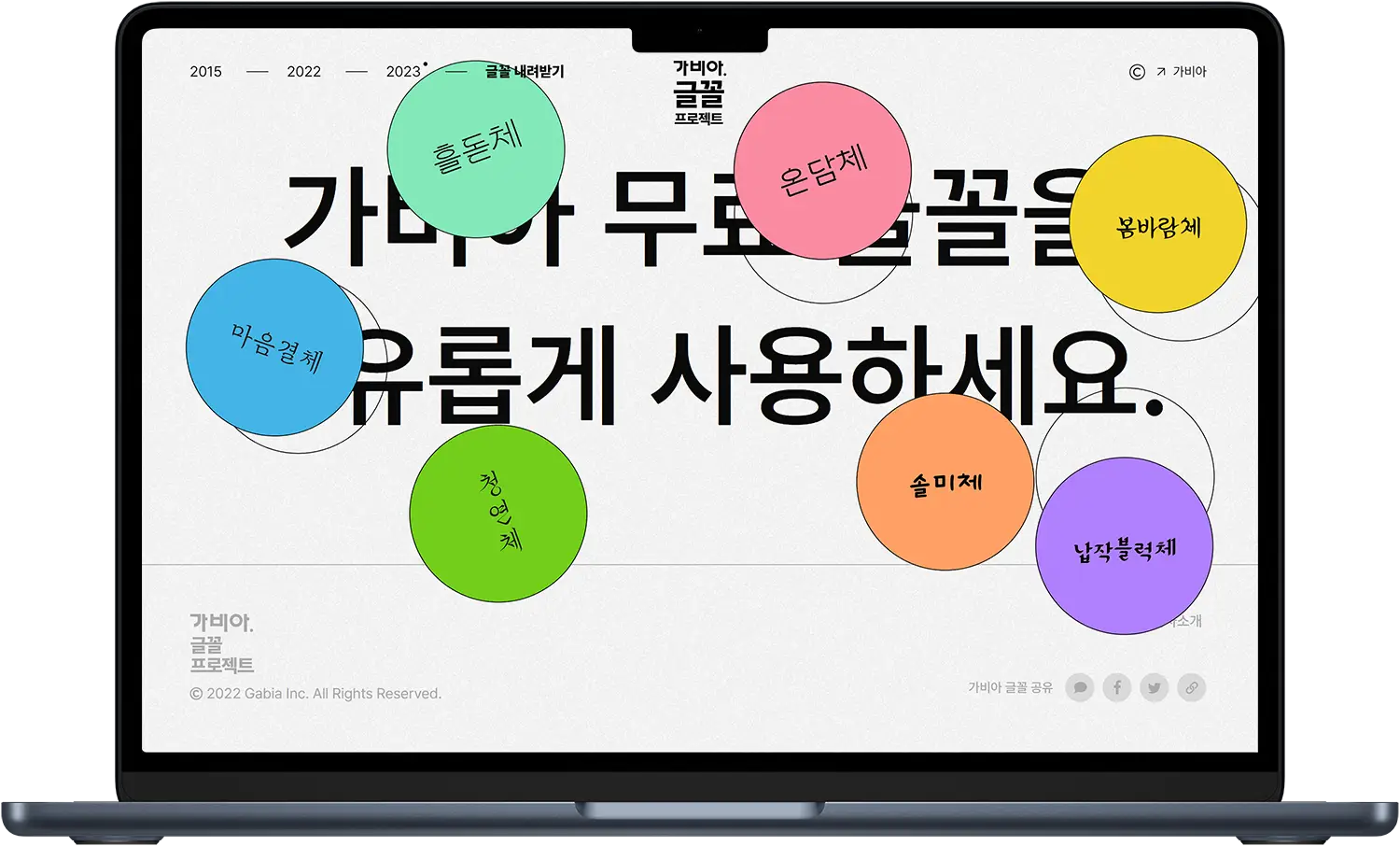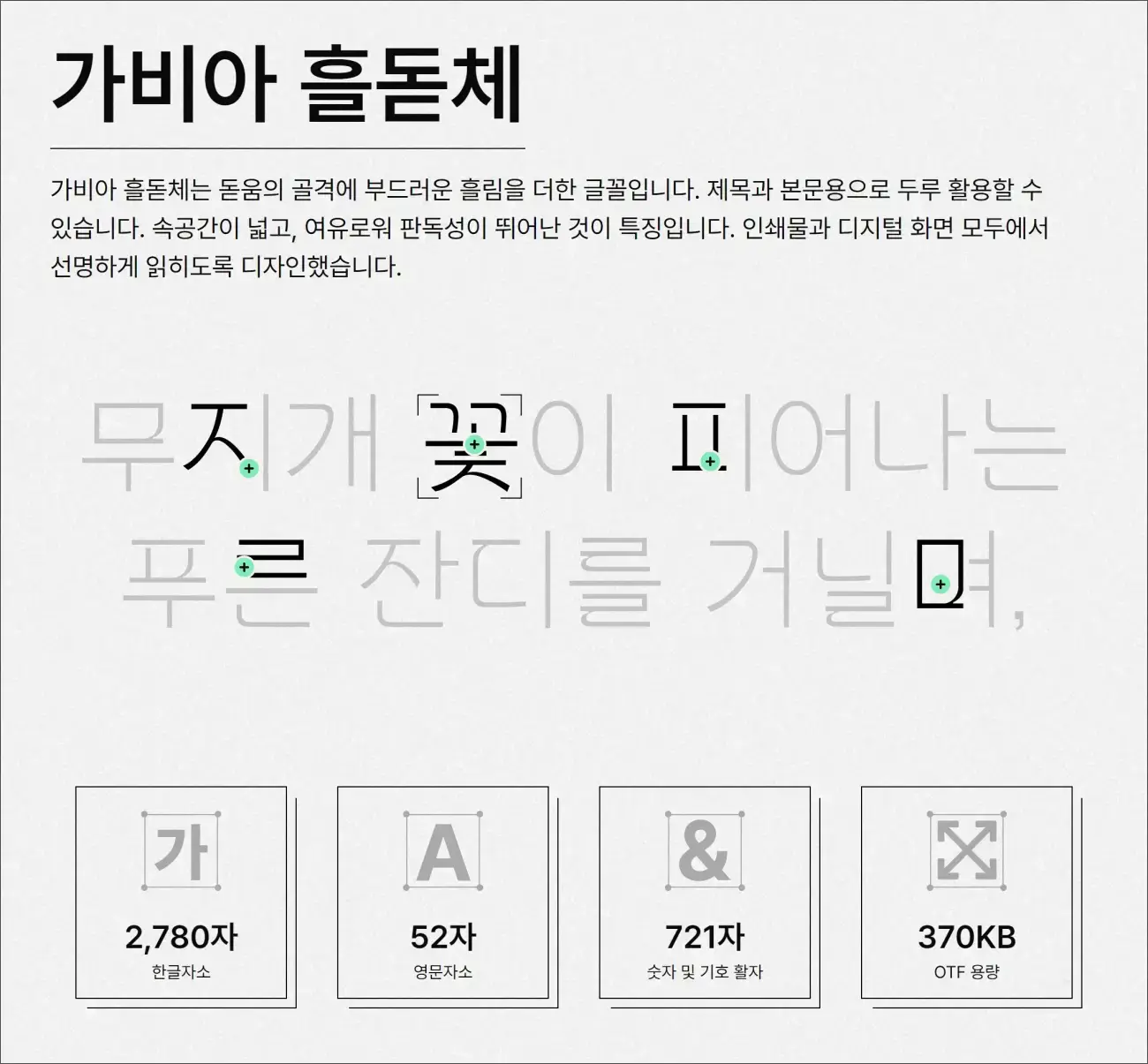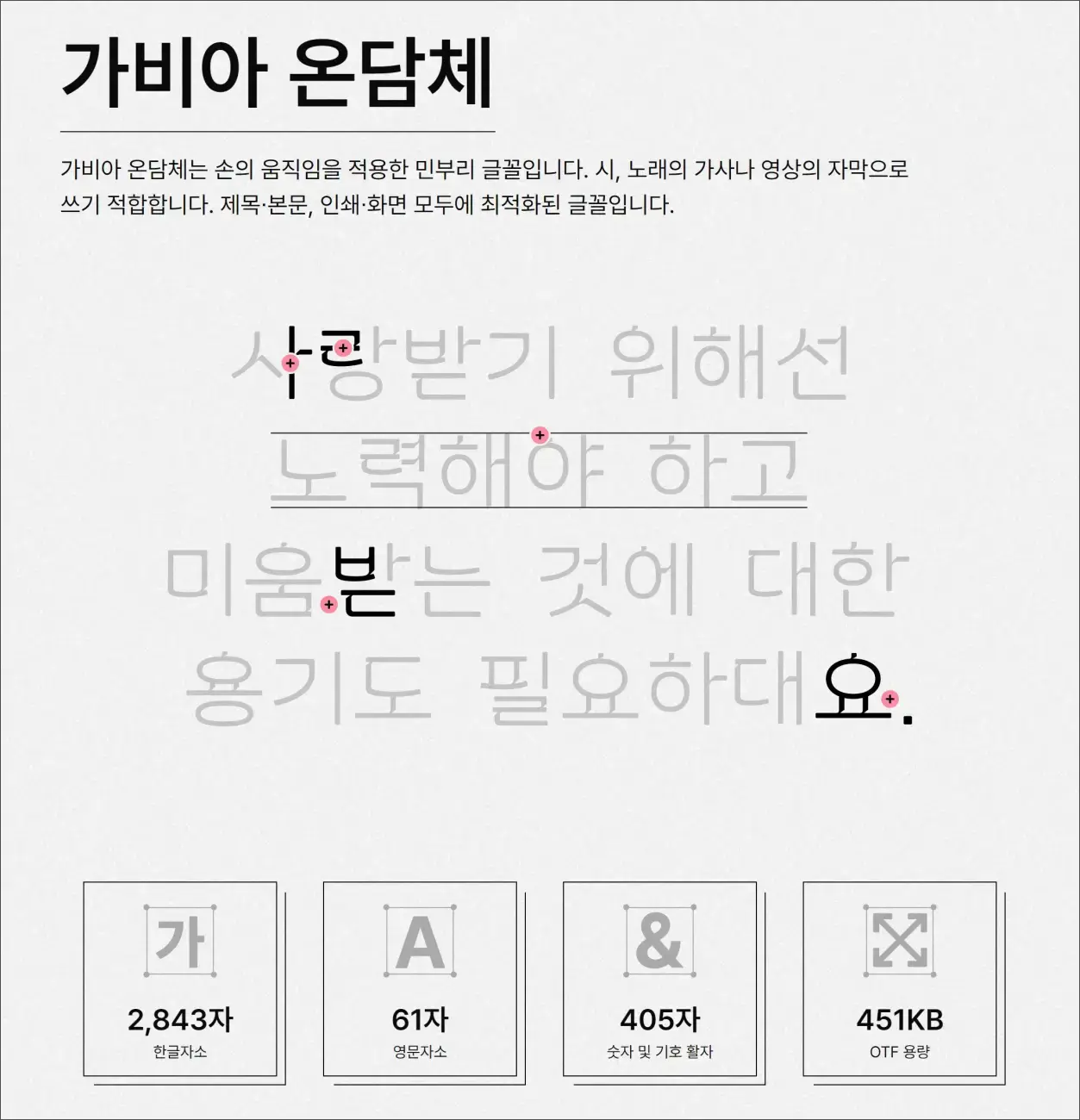
"가비아 흘돋체, 온담체 무료 다운로드 한글폰트 상업적 사용 가능"
클라우드 전문 기업 가비아는 '가비아 글꼴 나눔 프로젝트'로 지난 2015년과 2022년에 이어 2023년에 가비아 흘돋체, 온담체 두 개의 무료 한글 폰트를 공개했습니다. 개인이나 기업 구분 없이 누구나 자유롭게 상업적 목적에도 사용할 수 있지만, 글꼴 자체를 유료로 판매하거나 수정 및 재배포는 할 수 없습니다.
가비아 무료 한글폰트 흘돋체
가비아 흘돋체는 돋움의 골격에 부드러운 흘림을 더한 글꼴입니다. 제목과 본문용으로 두루 활용할 수 있으며 인쇄물과 디지털 화면 모두에서 선명하게 읽히도록 디자인되었습니다.
가비아 흘돋체는 한글자소 2,780자, 영문자소 52자, 숫자 및 기호 721자로 구성되어 있습니다.
정영훈 디자이너가 디자인한 흘린 돋움이라는 뜻의 ‘흘돋’은 돋움의 골격을 갖추면서도 손 글씨의 흐름을 담아낸 돋움체입니다. 제목과 본문용으로 두루 활용할 수 있습니다.
가비아 무료 한글폰트 온담체
가비아 온담체는 손의 움직임을 적용한 민부리 글꼴입니다. 시, 노래의 가사나 영상의 자막으로 쓰기 적합합니다. 제목∙본문, 인쇄∙화면 모두에 최적화된 글꼴입니다.
가비아 온담체는 한글자소 2,843자, 영문자소 61자, 숫자 및 기호 405자로 구성되어 있습니다.
‘가비아 온담’은 손의 따듯한 움직임을 담담하게 담아낸 민부리계열 한글서체입니다.